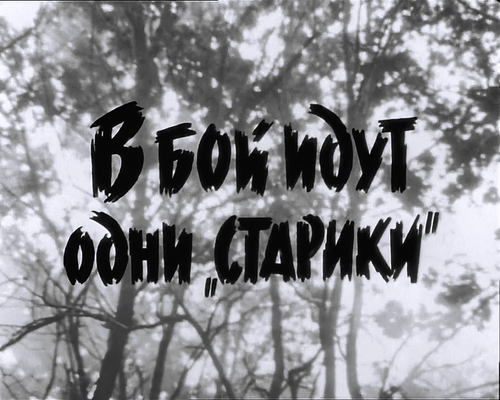
Kirill Опубликовано: 17 января 2016 Народ, если у кого-то есть в загашнике такой (или похожий) шрифт, поделитесь, плз.
Alambash Опубликовано: 17 января 2016 Видно же что это не шрифт. Вручную нарисована каждая буква.
=V=Felix_40 Опубликовано: 17 января 2016 Видно же что человек ищет похожий на это шрифт 2
NobbyNobbs Опубликовано: 17 января 2016 не совсем конечно, но типа кисть. DS Broad Brush http://lenagold.ru/tool/font/decor3.html 2
=2ndSS=JOCKER Опубликовано: 17 января 2016 Народ, если у кого-то есть в загашнике такой (или похожий) шрифт, поделитесь, плз. Тебе именно эта надпись нужна или весь шрифт ?
Kirill Опубликовано: 17 января 2016 Автор Опубликовано: 17 января 2016 (изменено) не совсем конечно, но типа кисть. Спасибо, Нобби. Тебе именно эта надпись нужна или весь шрифт ? Весь шрифт. Изменено 17 января 2016 пользователем Kirill